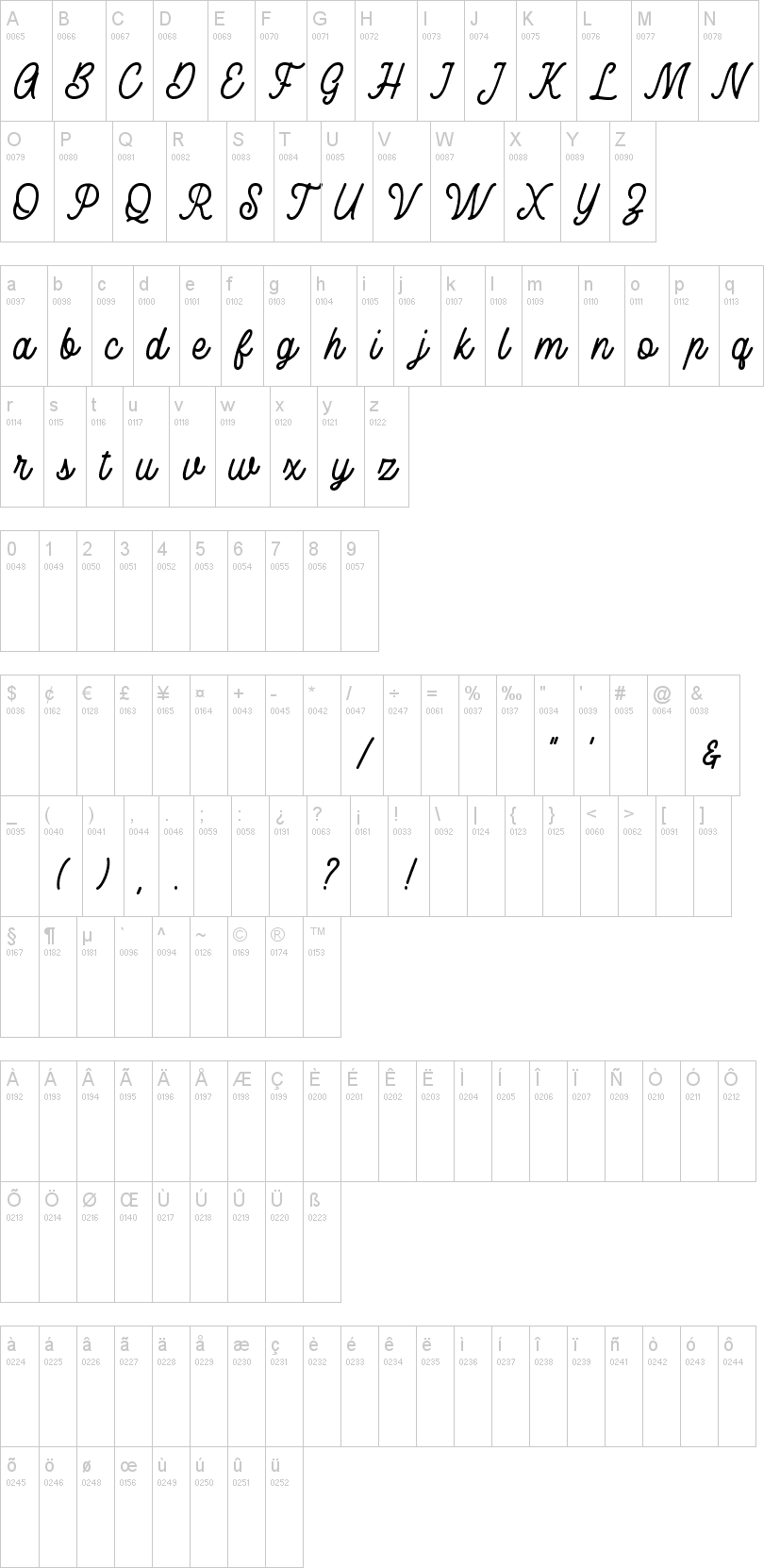
Rusted Orlando是一款复古风格的字体,它具有深厚的历史感和传统感,可以用于创造出一种独特的时尚和古典的外观。它的设计灵感来自于19世纪的美国南方,特别是佛罗里达州的奥兰多,它的字体特点是古老的复古风格,有着深厚的历史感和传统感,可以用于创造出一种独特的时尚和古典的外观。它具有良好的可读性和可视性,可以用于创造出一种具有历史感和现代感的外观。内容介绍
Rusted Orlando是一款非常不错的手写艺术字体,具有很好的视觉感,适合于文化类的宣传设计、商业类品牌的广告和产品包装设计以及个性化文字排版等较多场景。